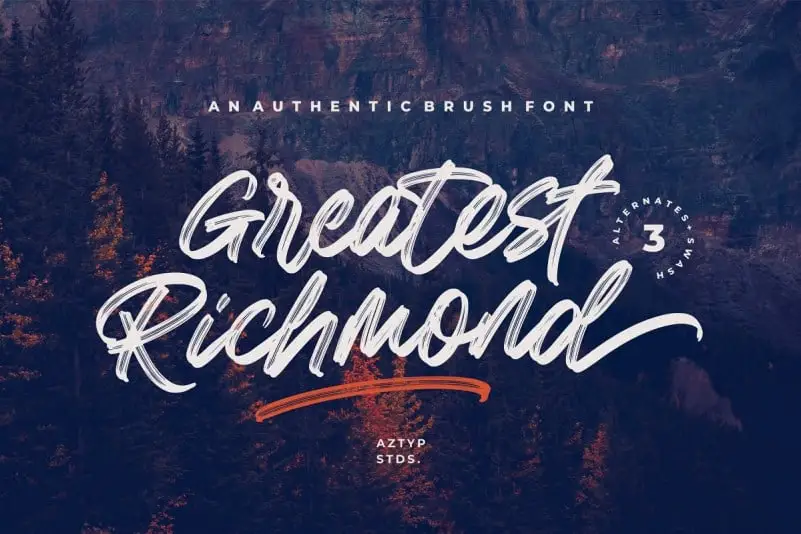
Greatest Richmond Brush Font – Fonte Grátis
Greatest Richmond Brush Font – Download Grátis
Greatest Richmond Brush Font
A fonte ‘Greatest Richmond Brush Font’ é uma excelente escolha para aqueles que buscam dar vida a seus projetos de design com estilo moderno e vibrante. Esta é uma fonte Brush com um efeito de traço que dá ao texto um toque despojado, esportivo e atemporal. Com três alternativas e 36 swashes únicos, esta fonte permite criar combinações personalizadas sem igual. Cada caractere é cuidadosamente combinado para garantir um resultado perfeito. A apresentação em alta resolução mostra a maneira como essa fonte pode se destacar em projetos de design modernos e criativos. Quer seja para uma revista, um site ou até mesmo um brochura, esta fonte está disponível para uso em qualquer projeto ou situação. Seu aspecto original torna-a perfeita para gráficos, identidades visuais e design editorial. Não importa o tamanho do projeto, ‘Greatest Richmond Brush Font’ oferece uma solução versátil e profissional de texto personalizado. Com apenas um clique, você transformará seu layout em algo realmente único e impressionante.